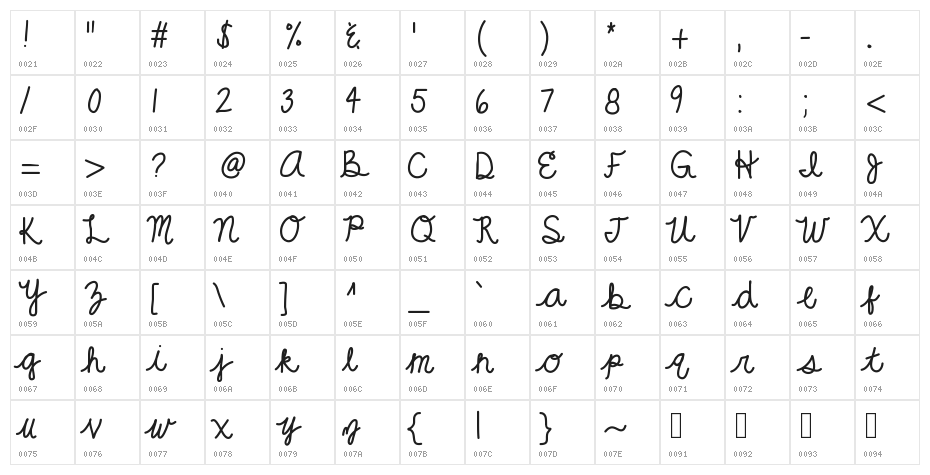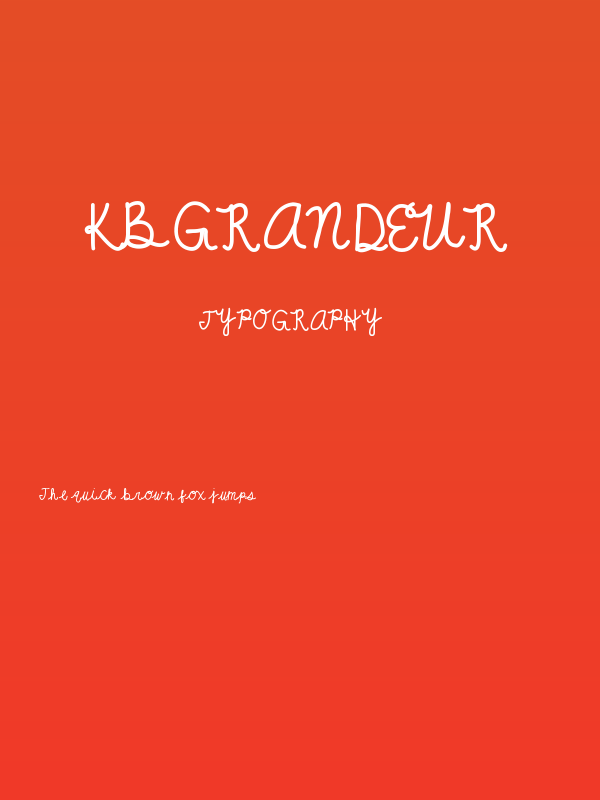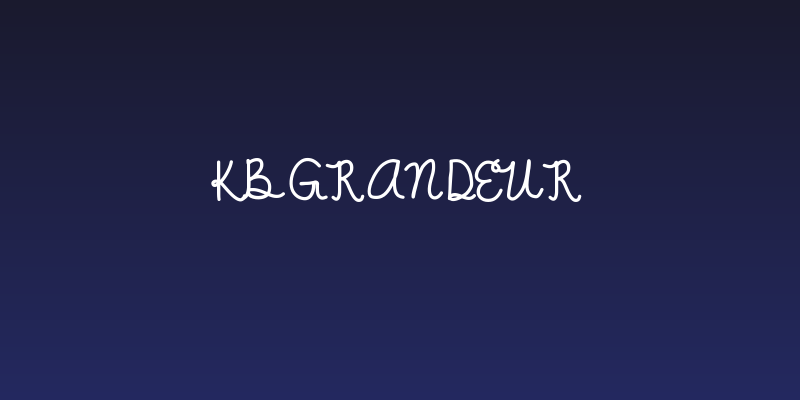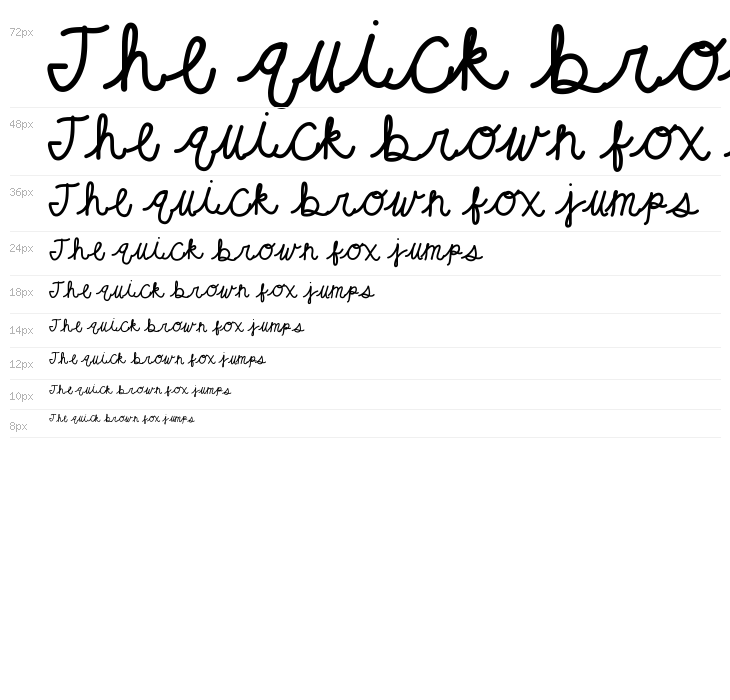
KBGrandeur Font
| Anwendungsfall | Logos, Invitations, Greeting Cards |
| Vorgeschlagene Projekte | Ideal for wedding invitations, greeting cards, personal branding, and creative projects that require a personal touch. |